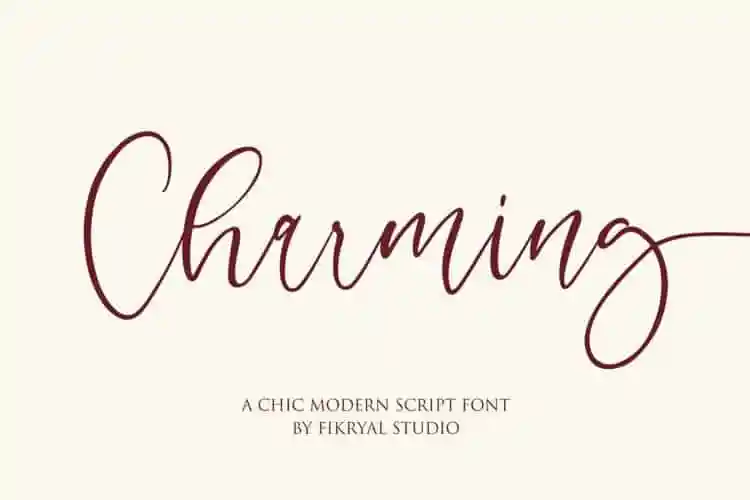
Charming – Modern Script Font – Download Grátis
Olha quem chegou! Introduzimos a você os novos produtos Charming Font, uma fonte escrita moderna e romântica perfeita para aqueles que valorizam um estilo elegante mas casual. Charming é uma fonte de script moderno que desperta o seu lado delicado. Com linhas fluidas e finalizações finas, esta fonte adora ser usada em logotipos, marca, títulos, postagens nas redes sociais, anúncios, embalagens de produtos, designs de produtos, etiquetas, fotografia, marcas, publicações na web, e muito mais. Seja o seu próximo projeto a ser apresentado, Charming tem um tom perfeito para ele. É uma fonte que combina elegância com simplicidade, uma mistura atemporal que se adapta bem à variedade de necessidades criativas. Escolha Charming para dar vida aos seus projetos visuais, e faça seu design brilhar!